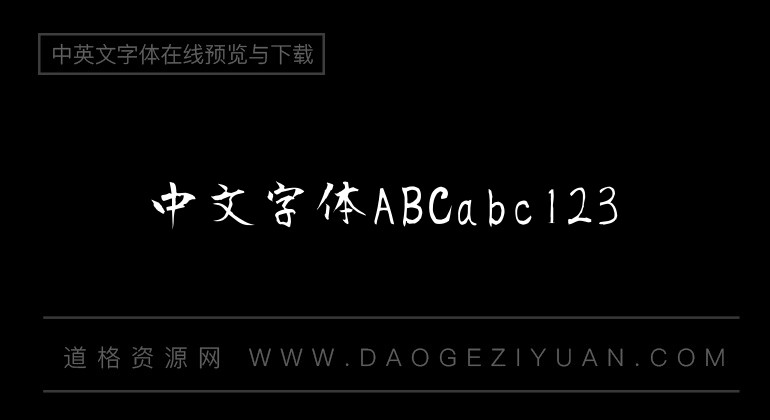
正风毛笔 Light 字体是一款中文毛笔字体,其特点是线条流畅、自然,配合细致的笔画描绘,显得干净、清新、雅致。此字体适用于书法、插画、海报、装饰等多种设计应用场景,尤其适用于注重简约、清新的现代设计风格。 此字体的设计灵感来自于中国传统毛笔字艺术,所以其字形和笔画都十分典雅。同时,正风毛笔 Light 字体也加入了现代设计中常用的一些元素,如平衡的排版、简单的线条、柔和的颜色搭配等,使其在传统与现代之间取得了完美的平衡。 总的来说,正风毛笔 Light 字体是一款非常适合视觉设计师和艺术爱好者使用的字体,它能够为设计作品增添一份文艺、清新的感觉,体现出设计者的个性和品味,更是一款展现东方美学风格的优秀中文字体。文件名:MasaFont-Light-2.ttf
正风毛笔 Light是一款非常不错的手写艺术字体,具有很好的视觉感,适合于文化类的宣传设计、商业类品牌的广告和产品包装设计以及个性化文字排版等较多场景。